印刷术可以使演示文稿成败。您可以花几个小时来处理模板和颜色,但是如果选择难以辨认或时髦的字体,可能会损害您的演示文稿。
在专业设置中,选择能够传达严肃感而又不失严肃感的字体很重要。好玩的。这种平衡很难实现。但是,无论您是在PowerPoint还是其他替代方法之一中创建演示文稿,以下免费的Google字体都是完美的专业演示文稿。
Serif字体与Sans-Serif字体
字体(或字体)主要分为两类:衬线字体和无衬线字体。衬线在拉丁语中是尾巴。衬线字体是在字母末尾有笔触的字体。 Times New Roman是流行的衬线字体的最佳示例。
Sans代表没有。因此,sans-serif字体是一种在字母末尾没有笔触的字体(例如Helvetica或Arial)。
对于专业的办公演示,最好使用sans-serif字体。但是某些新时代的衬线字体也可以很好地用于标题幻灯片。它们完美地补充了现代无衬线。如果您感到好奇,请阅读我们的印刷术术语指南,以更好地理解它们。
1。 Playfair Display
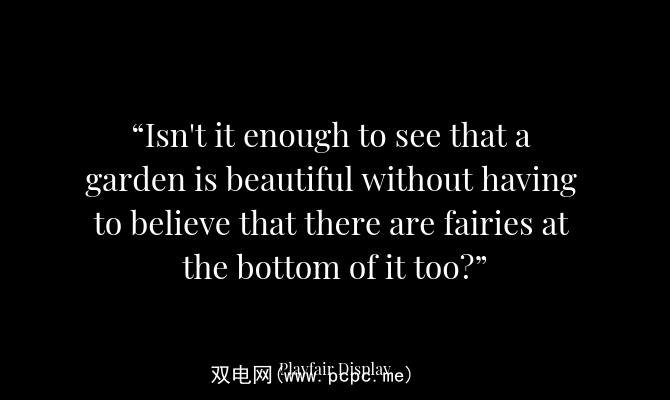
Playfair Display是一种衬线字体,带有一些个性。它可以追溯到18世纪后期的欧洲启蒙时代,当时用笔尖的钢笔代替了宽大的笔尖。这样就给Playfair带来了优雅,女性化的感觉。与乏味的Serif字体(例如Times New Roman)形成鲜明对比。
Playfair Display可以使标题文字更加美观;
非常适合:打开Sans
2。 Arvo
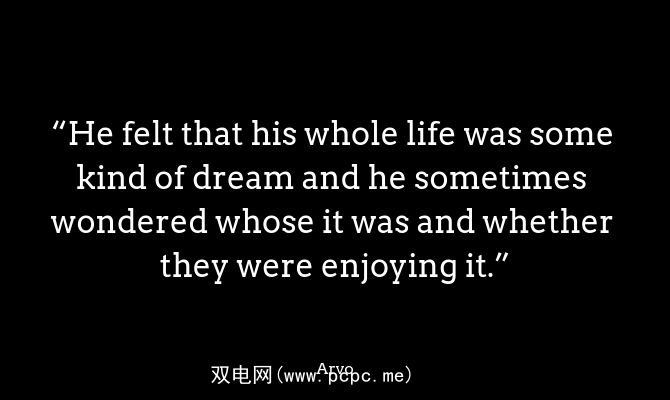
Arvo是一种为完美而设计的平板衬线字体。这是一种几何字体,融合了经典与现代。 Arvo Regular是平板衬线的一种较薄的现代版本,而Arvo Bold具有较粗的笔触和尖角。
Arvo Bold在较大的字体时效果最好,可作为商务或公司相关演示文稿的标题。与正确的颜色搭配时,Arvo可能会非常强大。
与非常匹配:Lato
3。深红色
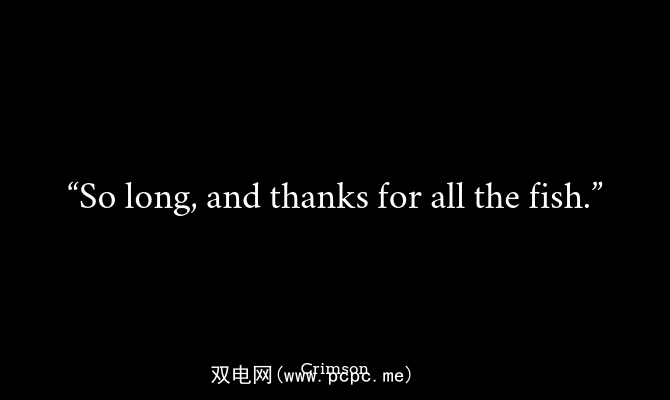
您不能对许多字体这么说,但是深红色的字体非常漂亮。如果您想通过经典却又有趣的演示使观众眼花,乱,请考虑使用深红色的标题和字幕。
深红色是受Garamond字体启发的sans-serif字体,但它不仅仅可以那。它是对传统旧字体的一种现代诠释,从头开始设计,以在屏幕和网站上看起来不错。如果您厌倦了在演示文稿中使用Times New Roman,请切换到深红色。
与完全匹配:蒙特塞拉特
4。打开Sans
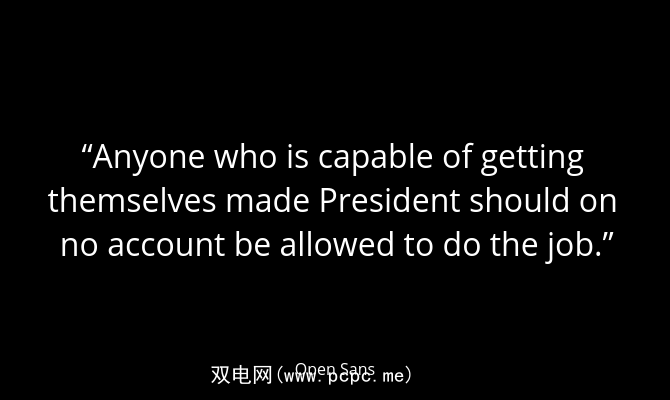
准备进行专业的演示时,首要规则是避免在文本上插墙。即使是要点列表也可能太多。但是,如果您需要几行内容来解释某些内容,或者如果您想以幻灯片的形式引用一长串,请尝试使用Open Sans。
Open Sans是开源的人道主义主义者Sans-衬线字体。它是字体的典型功能,在使用段落文本时几乎可以在任何情况下正常工作。即使是小字体,它也是清晰易读的字体。字体的半粗体版本与标题字体一样有效。
与非常匹配:Raleway
5。 Lato
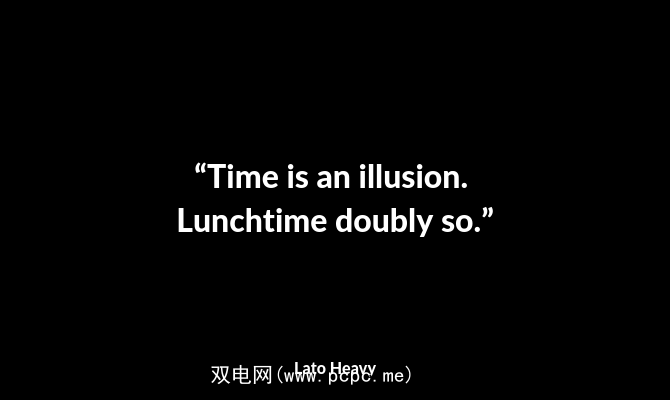
Lato在波兰语中是Summer,这种字体确实感觉像初夏的微风。当您仔细查看字体时,令人惊讶的是,根据开放源代码许可,如此注重细节的字体是免费提供的。
Lato由一家大公司委托作为字体,后来决定往另一个方向走。然后Lato变成了免费字体。您可以在这里看到其公司根源。字体具有半圆角细节,但仍很专业。 Lato字体家族千差万别,从Hairline版本一直到Heavy and Black。
由于Lato被设计为通用字体,因此它既可以用作段落文本,也可以用作标题字体。 。
很好地配合:在Raleway上打开Sans
6。蒙特塞拉特(Montserrat)
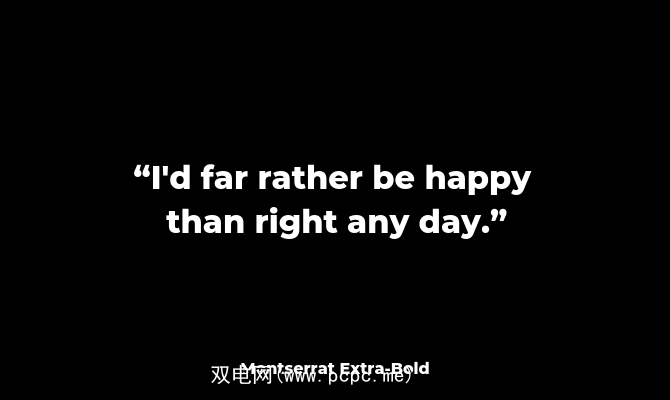
设置在Extra Bold中的蒙特塞拉特(蒙特塞拉特)是在专业演讲中传达年轻和前瞻性思维的理想方式。蒙特塞拉特(Montserrat)是一种字体,您经常会在技术创业公司的登录页面中找到它们。该字体的灵感来自布宜诺斯艾利斯蒙特塞拉特(Montserrat)社区的旧海报和标志。
由于其几何形状,蒙特塞拉特(Montserrat)是与其他sans-serif字体非常匹配的字体之一。例如,位于Bold的蒙特塞拉特(Montserrat)将与Open Sans和Lato一起使用。
与配对::Open Sans
7。 Merriweather
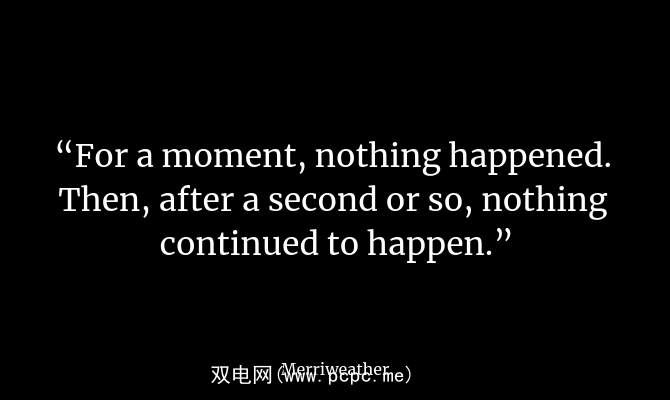
Merriweather是一种衬线字体,设计用于在屏幕上阅读。它是传统的衬线字体,但有更多的呼吸空间。字母本身被压缩,具有更高的x高度,在字母之间留出更多空间。
对的搭配很好:打开Sans,Roboto
8。 Abril Fatface
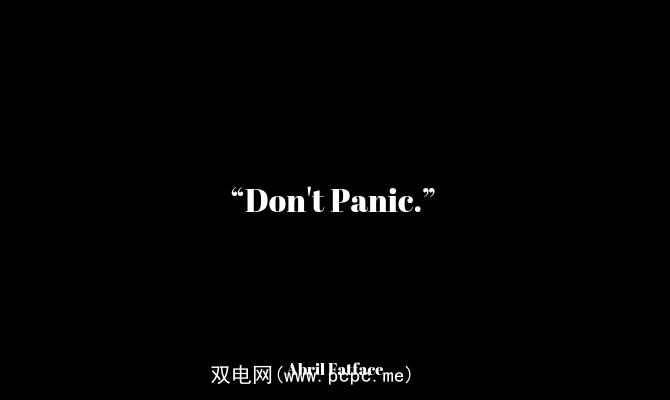
Abril Fatface是Abril大家族的一部分,拥有18种不同的字体,从显示版本到文本版本。 Fatface版本并不适合所有人。实际上,它更多是一种风格选择。
它具有粗大的笔触和细细的衬线。这使字体具有独特的个性并在屏幕上具有强大的外观。它的衬线根使它引人入胜,而倾斜的笔触则赋予它嬉戏的感觉。如果您希望文本在保持专业外观的同时脱颖而出,请尝试使用Abril Fatface作为标题字体。
很好地配合:Raleway,Open Sans
9。 Ubuntu
将Ubuntu视为Open Sans的样式版本。它也是一种开放源代码的sans-serif字体。它的开发由Ubuntu Linux背后的公司Canonical资助(这是我们最喜欢的发行版之一)。
虽然Open Sans具有对称的圆角边缘,但Ubuntu从一个边缘就弯曲了笔触。这在“ u"和“ n"之类的字母中最明显。
与完全匹配:Open Sans,Raleway
10。 Raleway
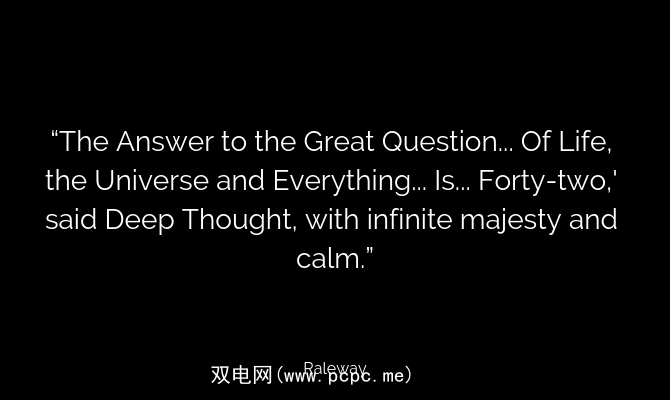
Raleway将衬线字体的优雅感引入了无衬线字体。这是一种设计用于标题的细字体,使其成为标题幻灯片的理想字体。
如果发现常规版本太细,可以尝试使用半粗体版本。
很好地配合:Roboto,Merriweather
了解字体配对的技巧
设计演示文稿最重要的方面不是过度地做。只需选择一种或两种字体,然后在整个演示文稿中使用它们即可。颜色和模板也是如此。保持简单和一致。
如果您仍然对各种类型的字体感到困惑,并且对serif和sans-serif字体感到困惑,只需选择一个简单的sans-serif字体,例如打开Sans并坚持下去。
一旦您熟悉打字操作,就可以参加比赛。尝试使用sans-serif和serif字体的不同组合。将Crimson与Lato配对或将Playfair Display与Open Sans配对,看看是否可行。
字体配对可以快速轻松地在线完成。您甚至不需要在计算机上下载所有字体。使用诸如Google字体和字体对之类的网站来查找演示文稿的理想字体。